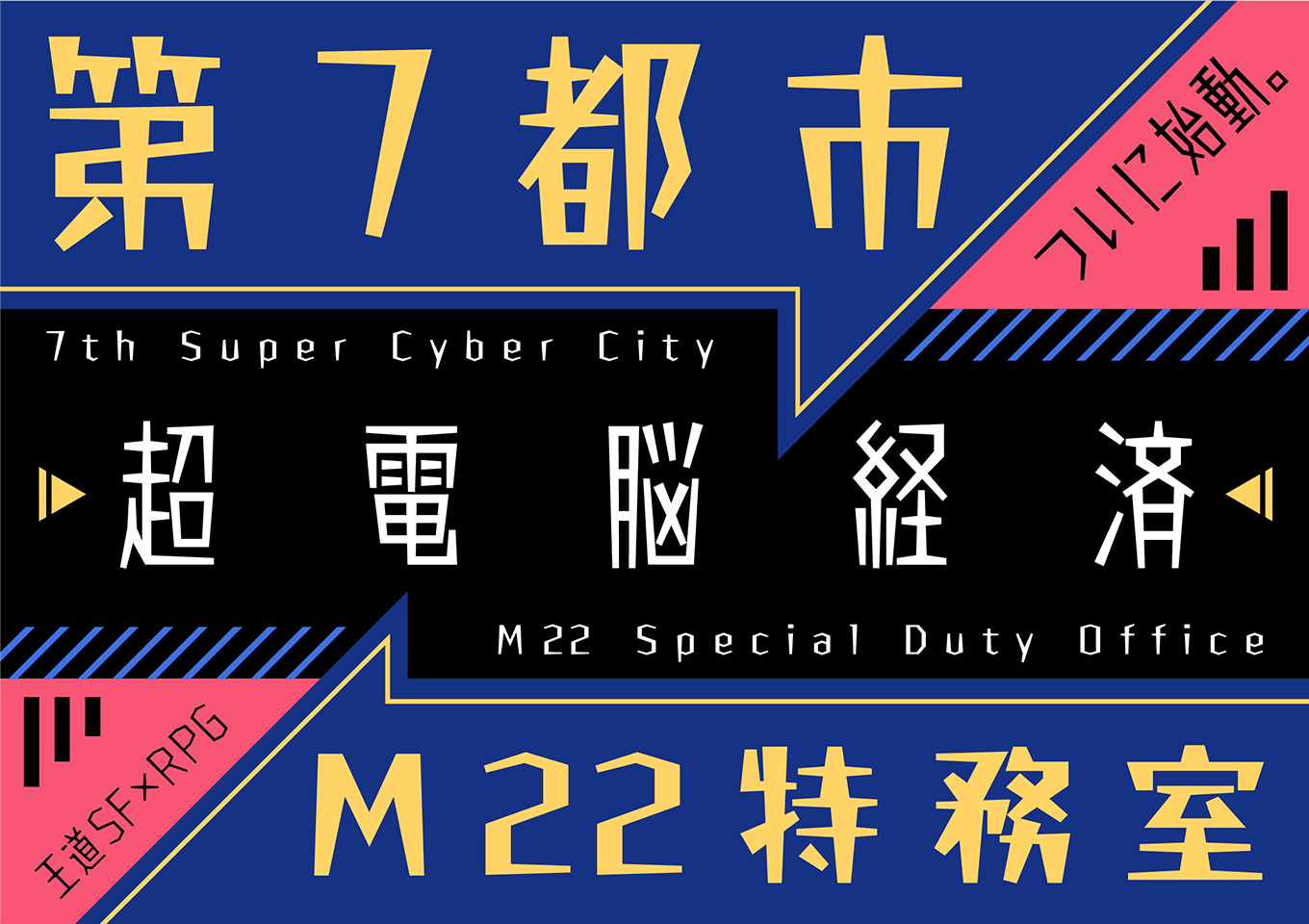
直線のみで構成されたシンプルな設計と、ウエイトごとに異なる字幅が特徴のデザイン書体です。Lは長体で緊張感のあるデザイン、Bは幅広で重厚感のあるデザインになっています。一部の文字では個性的な字形を採用し、ゲームやコミックなどコンテンツの世界観を演出するシーンでも活躍する書体です。
L / M / B
直線のみで構成されたシンプルな設計と、ウエイトごとに異なる字幅が特徴のデザイン書体です。Lは長体で緊張感のあるデザイン、Bは幅広で重厚感のあるデザインになっています。一部の文字では個性的な字形を採用し、ゲームやコミックなどコンテンツの世界観を演出するシーンでも活躍する書体です。
L / M / B